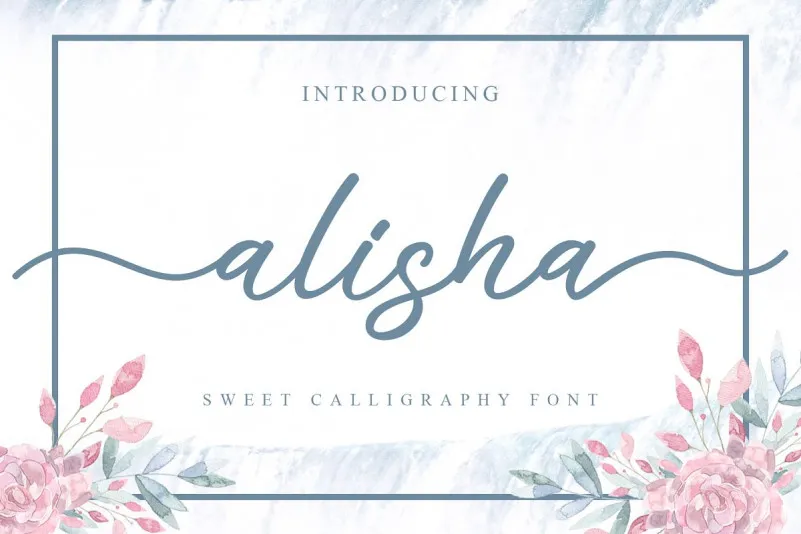
Alisha Sweet Calligraphy Font – Download Grátis
Alisha é uma elegante fonte de escrita cursiva que combina o refinamento moderno com a vivacidade do estilo retrô. Trabalhada manualmente, ela adota um tom simples e agradável, ideal para projetos gráficos diversos como desenhos de água-marinha em fotografias, frases personalizadas, capas de álbum, logotipos ou cartões de visita. Essa fonte única traz uma leveza ao seu trabalho de design, tornando-a perfeita para novos projetos criativos. Com sua base escrita ondulada e estilo moderno e elegante, Alisha é o tipo de font que não apenas destacará seus trabalhos, mas também os enriquecerá com um toque sofisticado. Se você está procurando por uma fonte de escrita cursiva para suas próximas criações de design, especialmente quando a delicadeza e elegância são essenciais, Alisha – Sweet Calligraphy Font certamente será seu melhor amigo no armário das fontes.